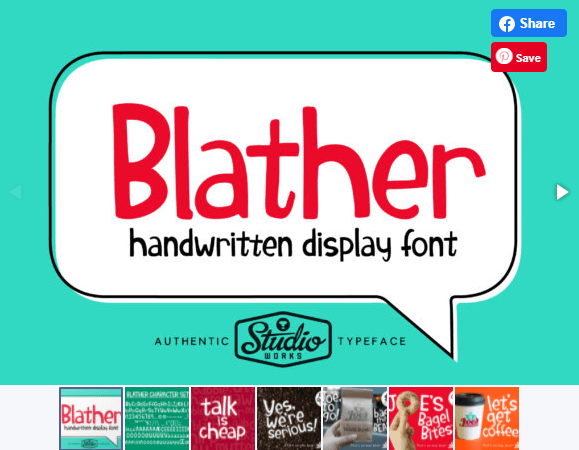
Blather Font
Blather - это причудливый дисплейный шрифт с непринужденной тематикой и прекрасным стилем. Независимо от темы, этот шрифт станет отличным дополнением к вашей библиотеке шрифтов, так как он может улучшить любое творение.